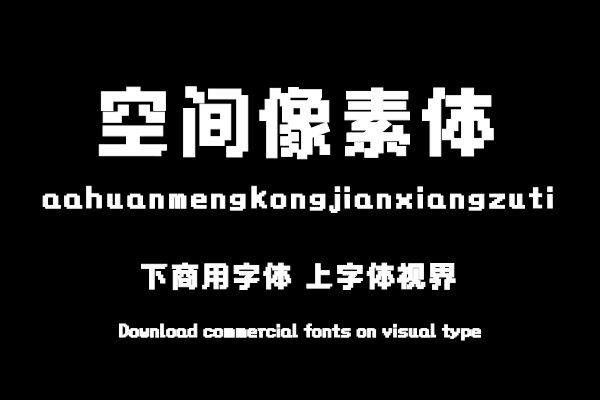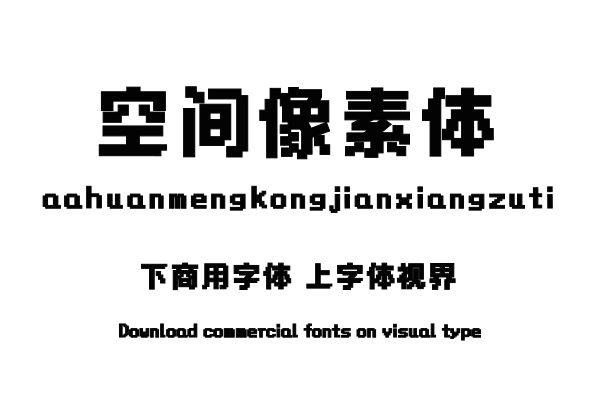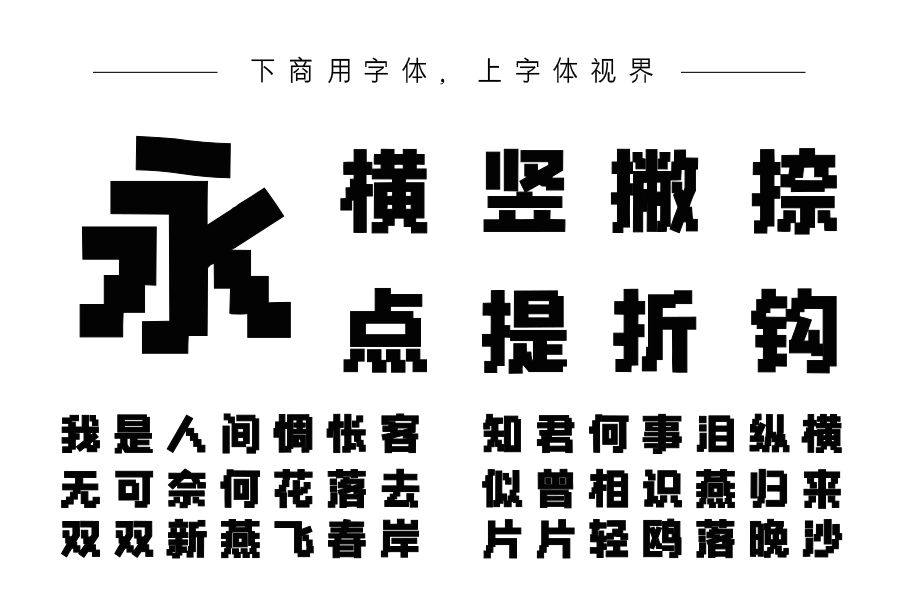
Aa幻梦空间像素体是一款以黑体为基础的像素字体,方块字形,整体风格硬朗,有一种科技复古感,适用于游戏、影视、运营、广告、海报等用途。购买须知:“下载服务费”与“字体VIP”所获得字体 仅用于个人非商用, 商用请联系付费授权。本字体为电脑用字,手机没有root权限不支持直接手机换字(手机如何root,请自行百度搜索教程)。购买前请先 了解清楚后再付款 ,字体为虚拟产品无法回收 一旦购买不支持退款。